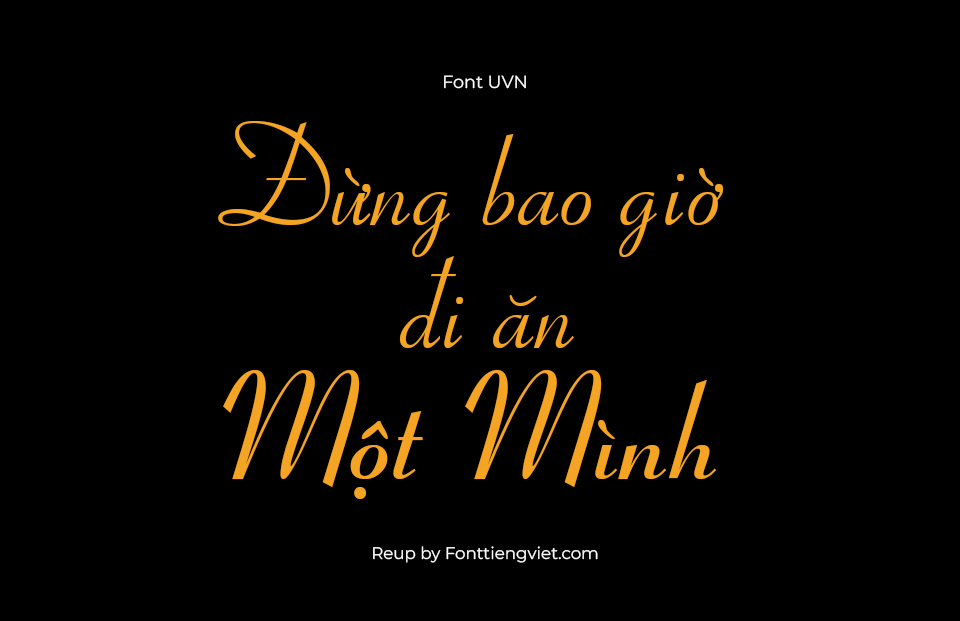
Tải Ngay Font Việt hóa UVN Kieu – Font Chữ Thư Pháp Mềm Mại Cho Thiết Kế
Giới thiệu bộ Font Việt hóa UVN Kieu
Trong thế giới đồ họa hiện nay, việc tìm kiếm một bộ Font Chữ mang đậm bản sắc văn hóa Việt là điều vô cùng quan trọng. Font Việt hóa UVN Kieu là một trong những đại diện tiêu biểu nhất cho phong cách thư pháp hiện đại. Được phát triển dựa trên cảm hứng từ những nét bút lông uyển chuyển, bộ phông này giúp các bạn học sinh và giáo viên dễ dàng tạo ra những ấn phẩm học đường đẹp mắt. Với sự chỉn chu trong cách xử lý dấu tiếng Việt, người dùng không còn lo lắng về lỗi hiển thị khi soạn thảo văn bản hay thiết kế biểu ngữ.
Những đặc điểm nổi bật của Font Việt hóa UVN Kieu
Phong cách thiết kế nghệ thuật
Sức hút của Font Việt hóa UVN Kieu nằm ở các đường nét thanh đậm hài hòa, gợi liên tưởng đến những tác phẩm thơ ca cổ điển như Truyện Kiều. Mỗi ký tự đều được chăm chút tỉ mỉ, tạo nên sự liền mạch và nhịp điệu riêng biệt. Điều này cực kỳ phù hợp cho các dự án thiết kế thiệp mời, bìa sách hoặc các slide thuyết trình cần sự trang trọng và tính thẩm mỹ cao.
Khả năng ứng dụng đa dạng
Không chỉ giới hạn trong các ấn phẩm in ấn, bộ font này còn hoạt động mượt mà trên nhiều phần mềm khác nhau từ Microsoft Office đến Adobe Photoshop. Với ưu điểm là bộ mã Unicode chuẩn, bạn có thể yên tâm sử dụng Font Việt hóa UVN Kieu mà không gặp khó khăn trong việc gõ dấu. Đây là công cụ đắc lực giúp nâng tầm phong cách thiết kế cá nhân một cách nhanh chóng.
Kết luận và trải nghiệm sử dụng